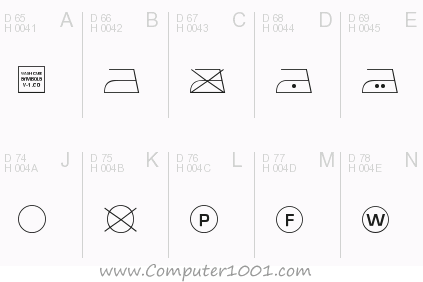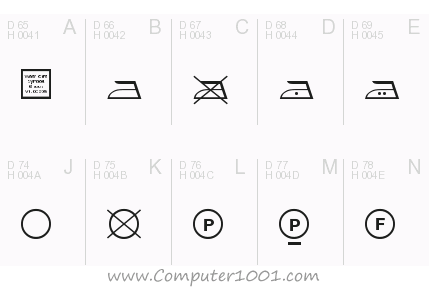
Artikel ini menyajikan kumpulan font dan vektor gambar yang bisa di-download gratis untuk membuat petunjuk pencucian (wash care / laundry symbol) pada label pakaian.
Font dan vektor berisi simbol-simbol yang umum dicantumkan pada label petunjuk perawatan pakaian, yaitu:
- Petunjuk pencucian pakaian
- Pemakaian pemutih pakaian
- Petunjuk pengeringan atau penjemuran pakaian
- Petunjuk menyetrika pakaian
- Petunjuk pencucian pakaian dengan metode dry cleaning
Font dan Vektor Petunjuk Pencucian Pakaian
- Washicons – Common Care Symbols
Simbol pencucian dan perawatan pakaian dalam bundelan file berisi font yang bisa digunakan sebagai web font dan icon gambar dalam format SVG serta PNG, mulai dari ukuran 32 x 32 pixel hingga 256 x 256 pixel. Juga memiliki gambar-gambar yang berhubungan dengan pencucian, seperti mesin cuci, keranjang pakaian, dan lain-lain.
- Washing Symbol Vector Pack
Vektor simbol cara mencuci dan pengeringan pakaian dalam format Ai (Illustrator).
- Wash Care Symbols M54
Font gambar untuk membuat simbol petunjuk pencucian dari M54.
- Wash Care Symbols Classic M54
Variasi lain dari M54 untuk font gambar petunjuk pencucian dan perawatan pakaian.